2023 年 15 种最佳西里尔字体(免费和付费)
已发表: 2023-09-09您是一名平面设计师,正在寻找完美的西里尔字体来提升您的项目吗? 好吧,别再看了! 在这篇博文中,我们将探索 2023 年 15 种最好的西里尔字体,包括免费和高级选项。
现在,让我们深入探讨这篇博文的标题:“2023 年 15 种最佳西里尔字母字体(免费和付费)”。 在这份综合指南中,我们将向您介绍 15 种出色的西里尔字母字体,它们将把您的设计项目提升到一个全新的水平。
我们知道,为您的项目找到合适的字体可能非常耗时且令人难以承受,特别是在涉及西里尔字母字体时。 因此,我们精心策划了此列表,以节省您的时间并为您提供最佳的选择。
在整篇文章中,您可以找到有关每种字体的有趣统计数据和事实,例如其受欢迎程度、下载数量和用户评分。 这样,您可以轻松识别设计社区强烈推荐的字体。
因此,准备好发现一些令人惊叹的西里尔字体,并了解为什么它们值得在您的设计工具箱中占有一席之地。 让我们直接进入第一种字体,探索它的独特功能和多功能性。 你兴奋吗? 我们当然是! 让我们一起开始这个字体之旅吧!
最佳高级西里尔字体
希望将您的平面设计项目提升到一个新的水平? 我们精心挑选的最佳优质西里尔字母字体就是您的最佳选择。 改进项目的整体设计,并通过这些独特且视觉上令人惊叹的字体吸引您的受众。
莫拉
Moula 是一种具有几何风格的现代无衬线字体。 该字体共有 18 种不同的样式,包括 9 种直体及其匹配的斜体。 Moula 以其干净简约的设计,散发着优雅温馨的氛围,适合各种设计项目。
Moula 的突出特点之一是它的多功能性和易读性。 无论您是从事图形设计项目、网页设计、标牌还是企业品牌,这种字体都非常适合所有类型的显示使用。
它的设计具有足够的多功能性,可以适应不同的设计需求。
莱奥塔罗
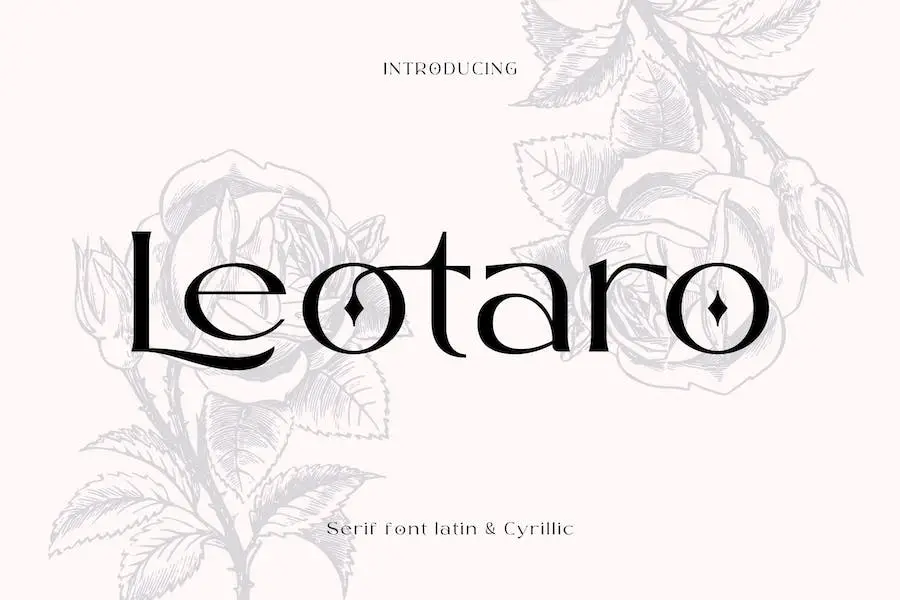
Leotaro 是一种衬线风格的字体,其灵感来自于 Reclaim 字体。 其简单而优雅的设计为任何平面设计项目增添了一丝精致感。 有了 Leotaro,您的创作将会给人留下深刻的印象。
这种字体充满了优雅和简洁。 Leotaro 源自 Reclaim 字体,将衬线之美提升到了一个全新的水平。 其简洁的线条和时尚的曲线为您的设计带来优雅和精致的感觉。
Leotaro 的与众不同之处在于它能够让您的项目令人难忘。 其独特的设计吸引了人们的注意,并对观众留下了持久的影响。
BD 巨蜥
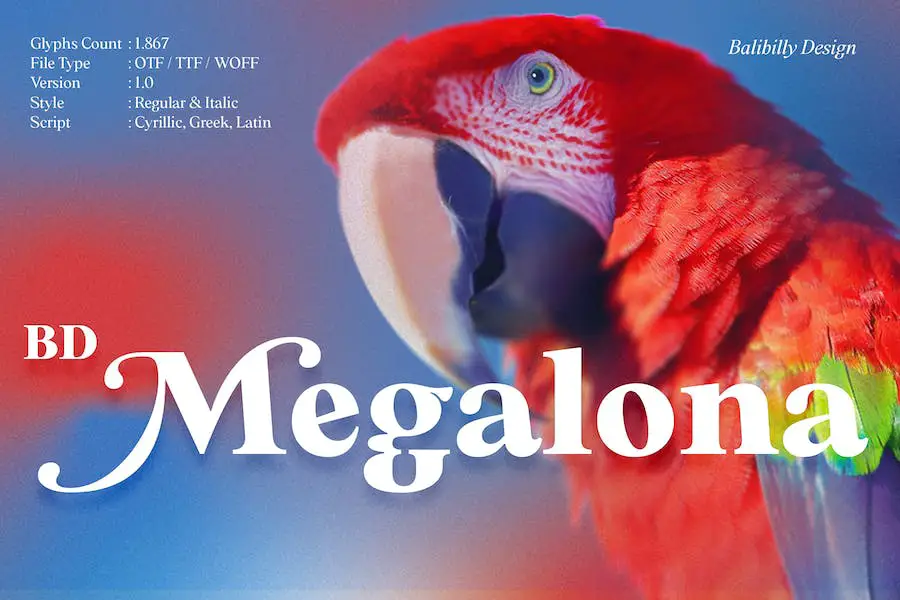
BD Megalona 是一款体现了精湛工艺和对细节的关注的字体。 这款字体具有一定的实验性和大胆的个性,旨在增强您的项目并使其真正脱颖而出。
其突出的功能之一是其广泛的字符集,其中包括 1800 多个字形并支持 219 种语言。 从拉丁字母到西里尔字母(基本到扩展)和希腊字母,这款字体都能满足您的需求。
BD Megalona 不仅提供广泛的语言支持,而且还拥有先进的开放式功能。
诗篇
Psalta 是一种现代 Blackletter 字体,具有细长、简洁的结构。 它提供了广泛的重量范围,从精致的发丝光到大胆而有力的版本。
该字体包含一整套西里尔字母,非常适合具有俄罗斯或东欧风格的项目。 此外,它还具有装饰重量,可以为字体添加装饰元素。
凭借其多功能性和对细节的关注,Psalta 是希望为其项目添加独特和时尚风格的图形设计师的绝佳选择。
赫尔姆斯瓦尔德邮报
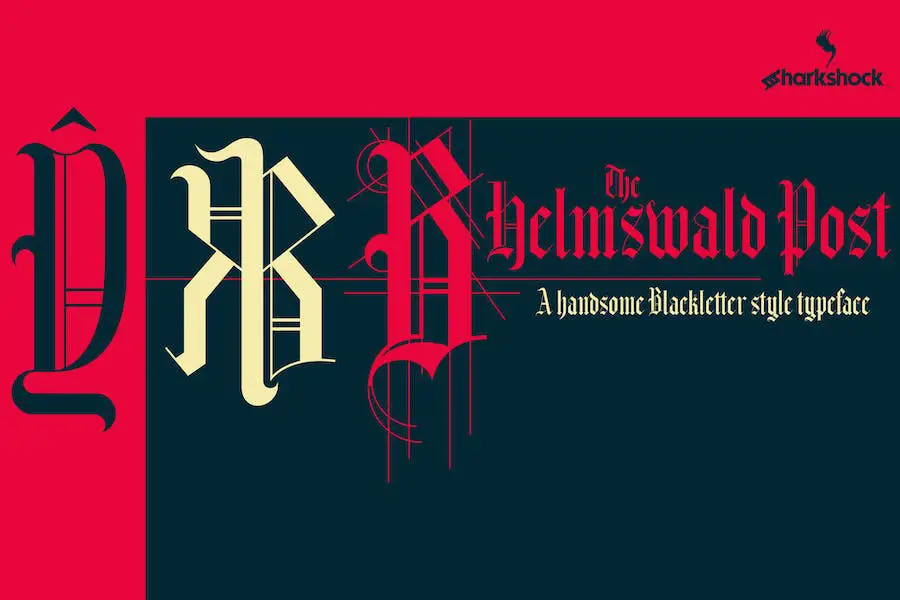
Helmswald Post 是一款漂亮的 Blackletter 字体,它将中世纪的文字与现代风格相结合。 它的特点是纤细的端子、华丽的盖子,并巧妙地利用负空间来创造对比。
这种独特的显示字体包括基本和扩展拉丁字符、标点符号、连字、欧洲口音、变音符号、替代符号以及俄语、乌克兰语和马其顿语的西里尔字符。
通过选择使用罗马大写字母或替代字母,您可以为您的设计添加更多多功能性。 另外,您还可以通过文体集访问旧世界的数字。 这是一种经过多年制作的字体,非常适合为您的项目增添一丝优雅和历史感。
潮流趋势
Afjat Trends 是一个名为 It Light 的尖端字体项目,旨在增强您的图形设计项目。
凭借其高对比度和现代风格,该字体非常适合品牌、徽标、邀请函、副标题、短语、文本等。 Afjat Trends 的窄矩阵可以轻松自定义和调整跟踪空间,特别是在较长的文本上。
其多功能性和时尚的设计使其成为寻求提升项目水平的平面设计师的首选。
尚宁线
SUNN Line 是一种字体,对于寻求提升其项目水平的平面设计师来说,它是一种游戏规则改变者。 SUNN Line 具有粗体和常规字重,提供了广泛的可能性。
它拥有广泛的字符集,包括拉丁字母、拉丁扩展字母和西里尔字母,以及大写和小写选项。
SUNN Line 的大胆重量为您的设计带来大胆而有影响力的外观。 其强劲的线条和引人注目的性质使其非常适合标题和突出的文字。
香蒜
“Pesto 是一种多功能且美观的字体,它将把您的设计提升到新的高度。 凭借其多语言功能,这种无衬线字体非常适合各种项目,从复古徽标和品牌到艺术海报和文章。
无论您想要增添一丝优雅还是一丝怀旧,Pesto 都能满足您的需求。
此外,它还支持多种语言,包括西班牙语、葡萄牙语、德语、丹麦语、法语、加拿大法语、意大利语以及西欧和中欧语言。
财富
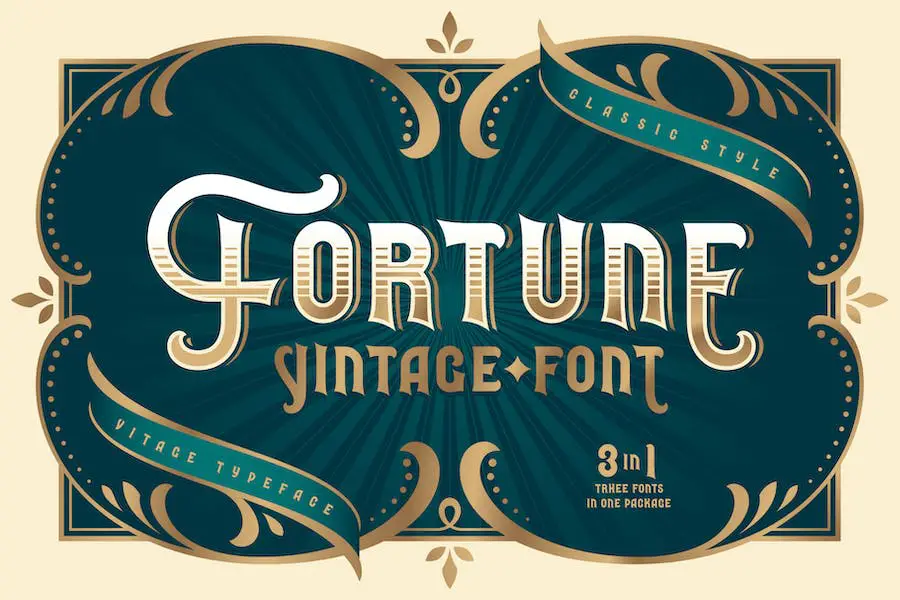
Fortune 是一款名为“It Vintage Font”的复古字体集,可为您的项目带来老式外观。 凭借其经典的西方形状,这种字体增添了一丝怀旧和真实感。
该字体具有三层,可以轻松重新着色和自定义以满足您的设计需求。 此外,所有小字母都有一两个替代选项,具有独特的底部扩展形状,为您的设计增添多样性和灵活性。
Fortune不仅支持大多数欧洲语言,还包括乌克兰西里尔字符,使其适用于广泛的项目。
维吉尔
Virgil 是一种复古的拉丁文和西里尔文字体,可为酒精标签和徽标等项目增添一丝优雅。 以其装饰风格,为任何设计带来独特的魅力。
无论您是为精酿啤酒制作标签,还是为高端品牌创建迷人的徽标,这种字体一定会给人留下深刻的印象。
其多功能性使其可用于各种制作,为您的项目带来独特而经典的外观。 与 Virgil 一起为您的设计增添趣味,创造出真正非凡的作品。
最好的免费西里尔字母字体
您是一名平面设计师,希望使用一些令人惊叹的西里尔字母字体来增强您的项目设计吗? 别再犹豫了! 我们整理了一系列最好的免费西里尔字母字体,可将您的设计提升到一个新的水平。
今天就发现这些隐藏的宝石并提升您的创造力。 请查看下面我们精心挑选的字体,让这些字体给您带来启发。
印刷图形
TypoGraphica 是由 sharkshock 创建的名为“It Font”的字体。 对于想要增强项目设计的图形设计师来说,这种字体是必备的。 凭借其独特而时尚的外观,它为任何设计作品增添了创意和专业精神。
TypoGraphica 的突出特点之一是它的多功能性。 它与拉丁和西里尔字母兼容,适合必须使用不同语言的设计师或来自不同地区的客户。
无论您使用哪种语言,TypoGraphica 都能满足您的需求。
图书馆 凌晨 3 点
LIBRARY 3 AM 是一款引人注目的字体,由才华横溢的设计师 Igor Kosinsky 设计。 凭借其独特的风格和引人注目的特征,这种字体非常适合想要以复杂性增强其项目的图形设计师。
LIBRARY 3 AM 字体提供了广泛的属性,使其成为任何设计师的必备品。 其时尚而现代的设计为任何项目增添了现代气息,使其成为徽标、品牌材料和网站设计的理想选择。
该字体简洁的线条和清晰的边缘确保了可读性,而其大胆的设计增添了一种天赋和个性的元素。
萨尔玛·普罗
Salma Pro 是一种独特且多功能的字体,非常适合希望增强项目设计的图形设计师。 该字体由 Alifinart 创建,提供一系列属性,有助于将您的设计提升到一个新的水平。
使用 Salma Pro,您将可以访问各种西里尔字母字体。 这些字体经过专门设计,旨在为您的项目增添优雅、风格和精致。 无论您是在制作徽标、网站还是任何其他设计项目,Salma Pro 都能为您提供庞大的字体库。
Salma Pro 的突出特点之一是对细节的关注。 每个字母都经过精心制作和设计,以确保最佳的易读性和视觉吸引力。 这意味着您的设计不仅看起来很棒,而且易于阅读和理解。
夏布利
Zt Chablis 是一种多功能的西里尔字体,非常适合希望提升项目设计的图形设计师。 凭借其引人注目和时尚的外观,这种字体一定会增强您正在进行的任何设计。
这款字体由才华横溢的设计师 khaiuns 创建,对于那些寻求为自己的作品增添一丝优雅的人来说是必备的。
Zt Chablis 的显着特征是其西里尔字母,这赋予了它独特而鲜明的风格。 无论您是从事品牌项目、网站设计还是创作海报,这种字体都会为您的工作增添一丝精致和专业精神。
科尼
Coiny 是由 Denis Ignatov 创建的现代时尚的西里尔字体。 这种字体非常适合希望通过独特且具有视觉吸引力的字体来增强其项目的图形设计师。
凭借简洁的线条和现代的设计,Coiny 为任何项目带来优雅的气息。 无论您是设计宣传册、徽标还是网站,这种字体都一定能彰显个性。
Coiny 的突出特点之一是它的多功能性。 这种字体可用于广泛的设计项目,从企业品牌到广告活动。 其时尚和流线型的外观非常适合简约和大胆的设计。
经常问的问题
西里尔字母字体是一组专门为西里尔字母书写而设计的字体,用于俄语、保加利亚语、塞尔维亚语和乌克兰语等语言。
这些字体包括西里尔字母特有的字符,允许用户在数字平台上准确地表示这些语言的书面形式。
西里尔字母字体是一组专门为西里尔字母书写而设计的字体,用于俄语、保加利亚语、塞尔维亚语和乌克兰语等语言。
这些字体包括西里尔字母特有的字符,允许用户在数字平台上准确地表示这些语言的书面形式。
选择西里尔字母字体时,重要的是要考虑易读性、样式和兼容性等因素。 易读性是指字符的易读性,尤其是在较小尺寸或低分辨率屏幕上。
风格是个人喜好的问题,您可能希望选择与项目的整体设计和基调相符的字体。
兼容性至关重要,因为并非所有设备和平台都支持所有字体,因此必须选择广泛兼容的字体,以确保在各种媒体上正确显示。
结论
为了结束本文,我们讨论了 2023 年 15 种最佳西里尔字体。我们探索了免费和高级选项,为您提供了多种选择来增强项目的设计。